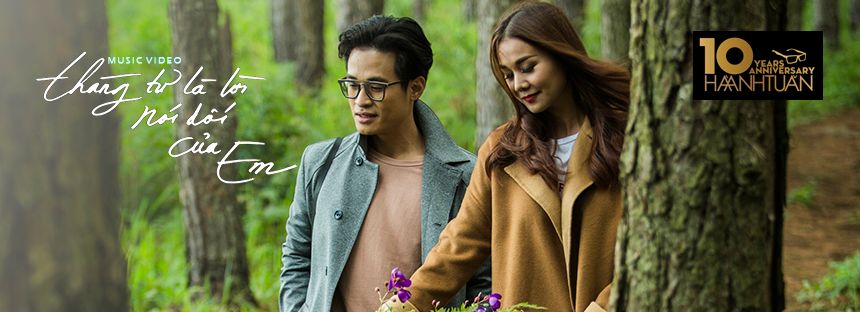
Cho hỏi font chử NEW WAVE
Các bạn cho mình hỏi font viết tay trong hình là font gì vậy?xin cảm ơn.
Đã tìm được roài, là Thư pháp Thiên Ân. Mod xóa Topic dùm mình nhé. Thanks mod!
Bạn nào biết 4 font chữ trong 2 hình bên dưới thì chỉ cho mình với, đang cần gấp mà tìm hoài ko được.
An - HTV Nếu thật sự bạn muốn tìm font thì vẽ lại mấy ký tự trên với nền đen chữ trắng mình sẽ giúp bạn :))
rungtram2014 ý bạn là thế này hả. Họ chỉ có cái file chất lượng kém, nhờ mình làm lại dùm file thiết kế để lưu thôi, bạn hiểu xa quá :D
myfont mình cũng đã tìm, chỉ tìm dc font chữ Rượu thôi. còn lại vẫn ko tìm dc
font rượu bạn cũng có sài font việt hóa tên là ( UTM Nyala )
có bạn nào có thể giúp mình ko, mình đang tìm một font thể hiện đc tính chất của chữ :" Cung đình Huế".